今回は、昭和書体の人気5書体(風神書体、雷神書体、龍神書体、文龍書体、昇龍書体)をパッケージにした昭和書体:最強お守り日本語フォント集です。
「昭和書体:最強お守り日本語フォント集」の気になる中身
風神書体
女性的なデザイン毛筆書体(フォント)です。
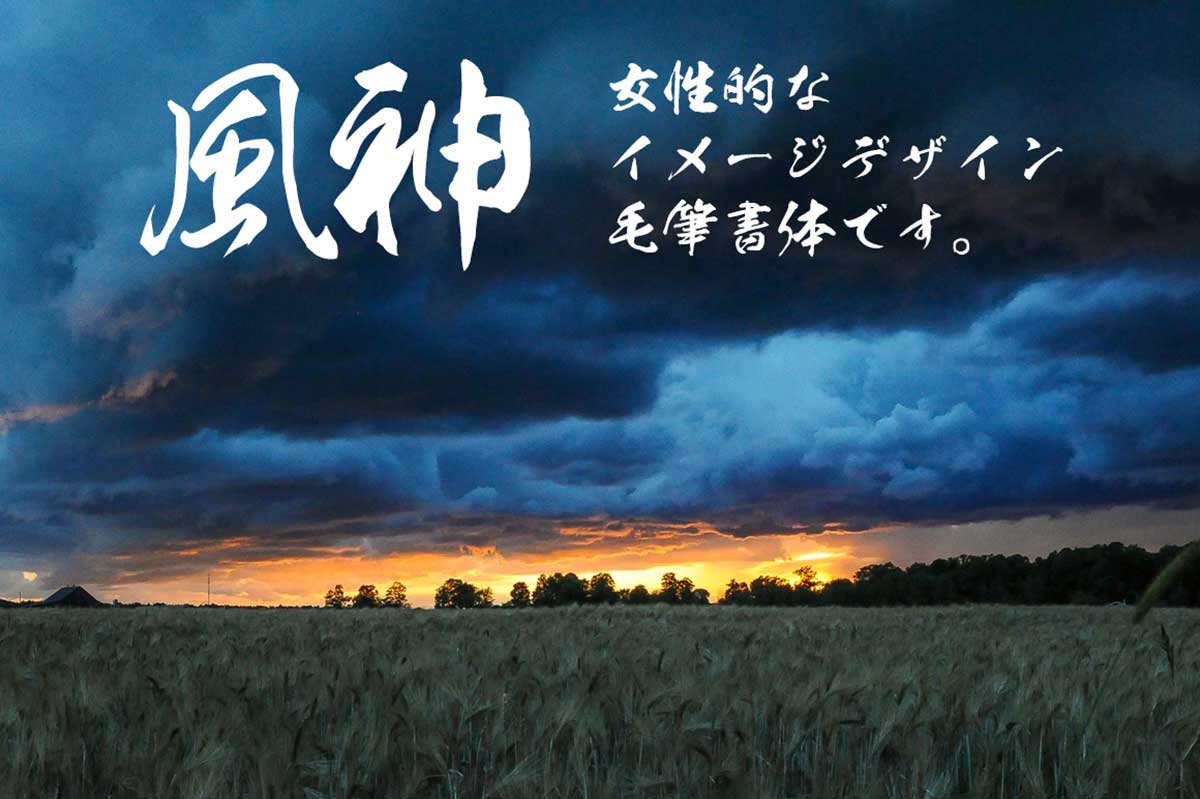
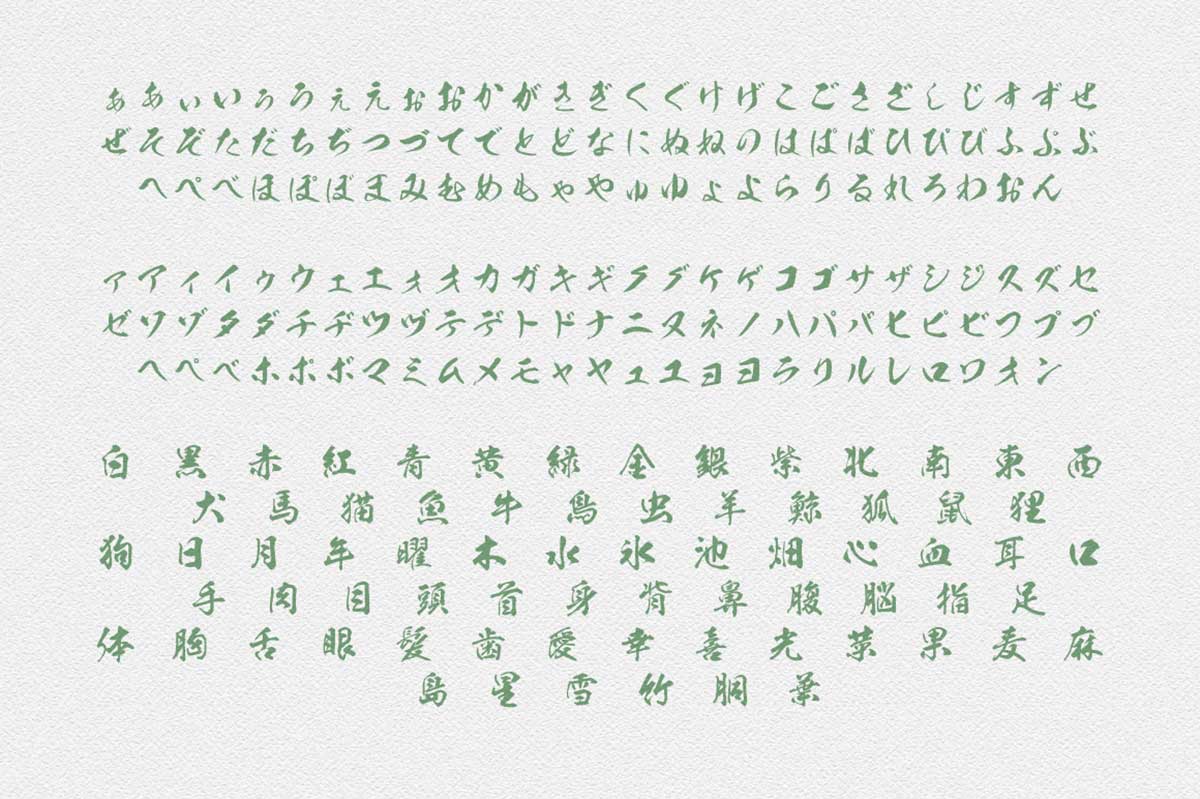
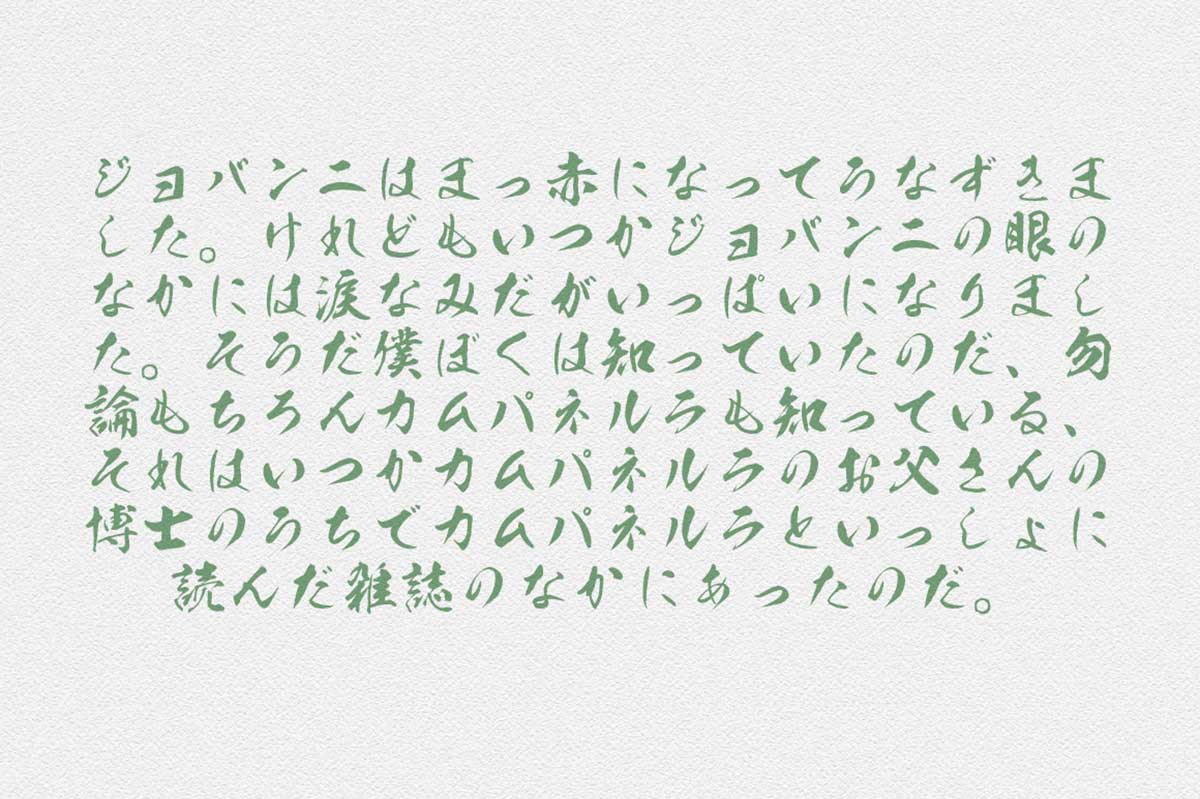
雷神書体
男性的なデザイン毛筆書体(フォント)です。
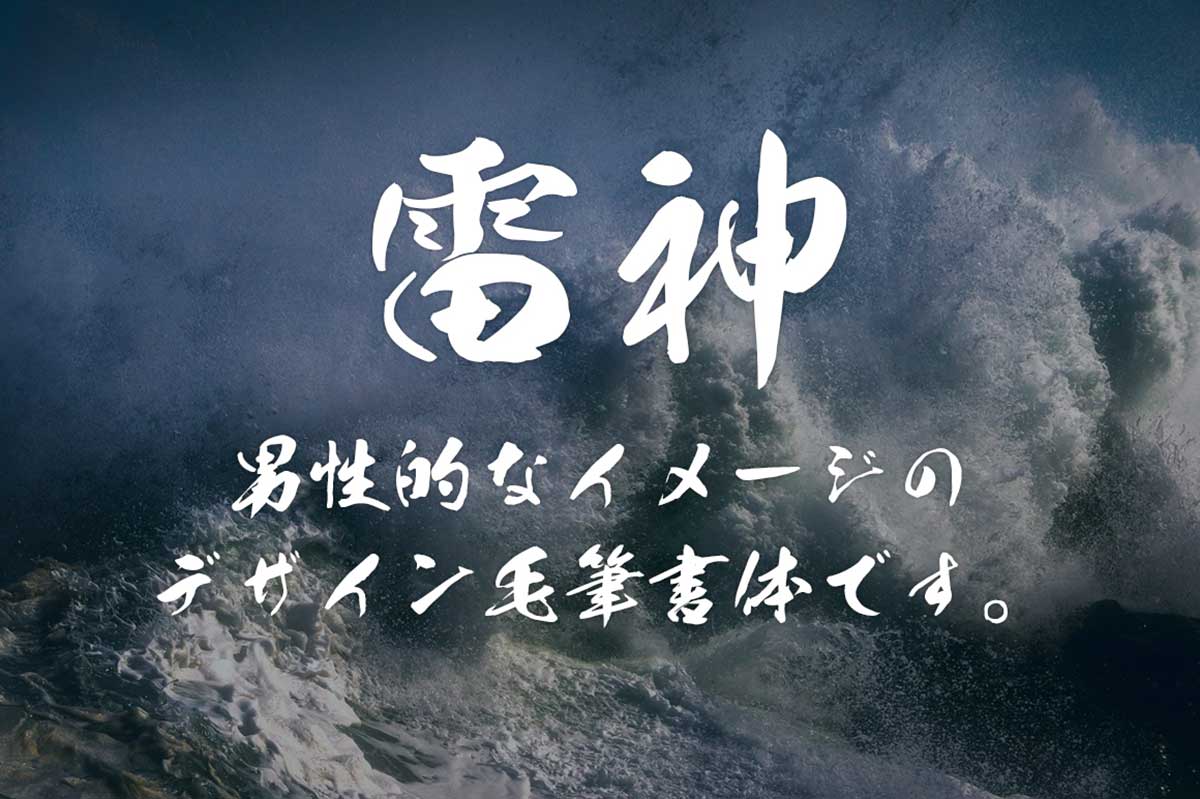
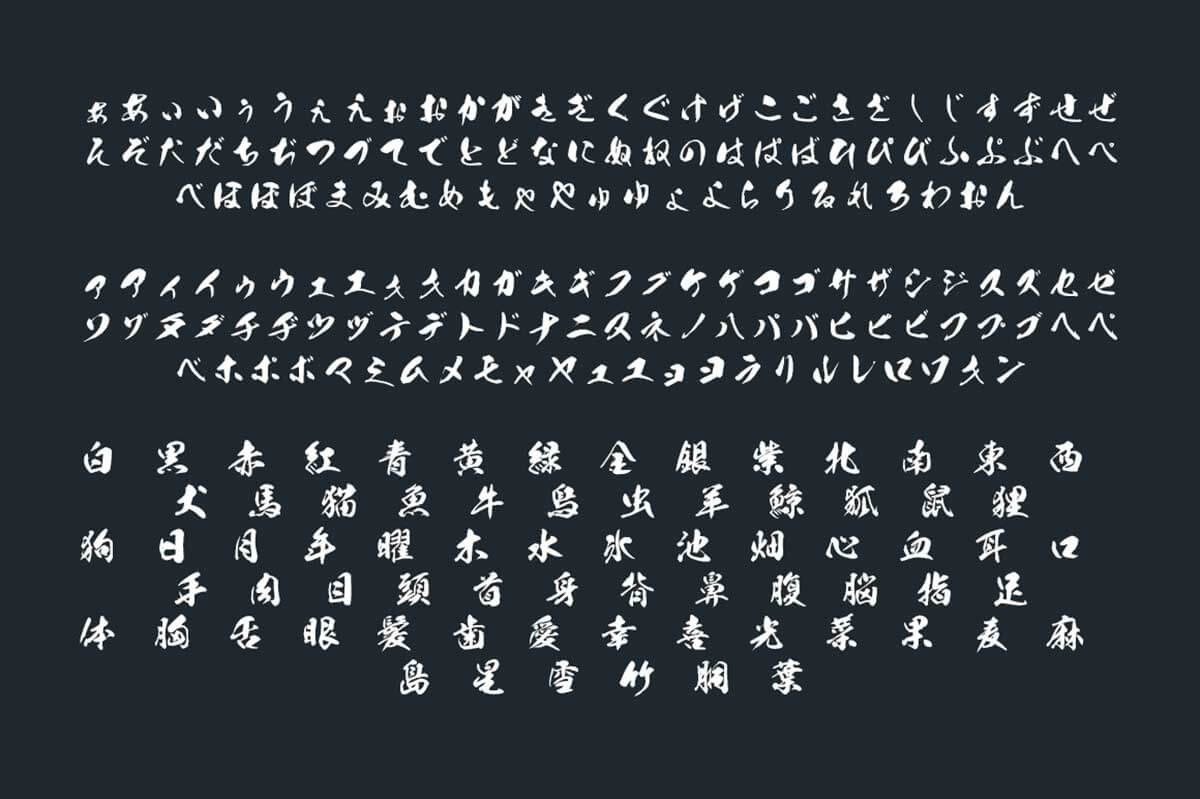
龍神書体
荒々しい龍を彷彿とさせる書体(フォント)です。
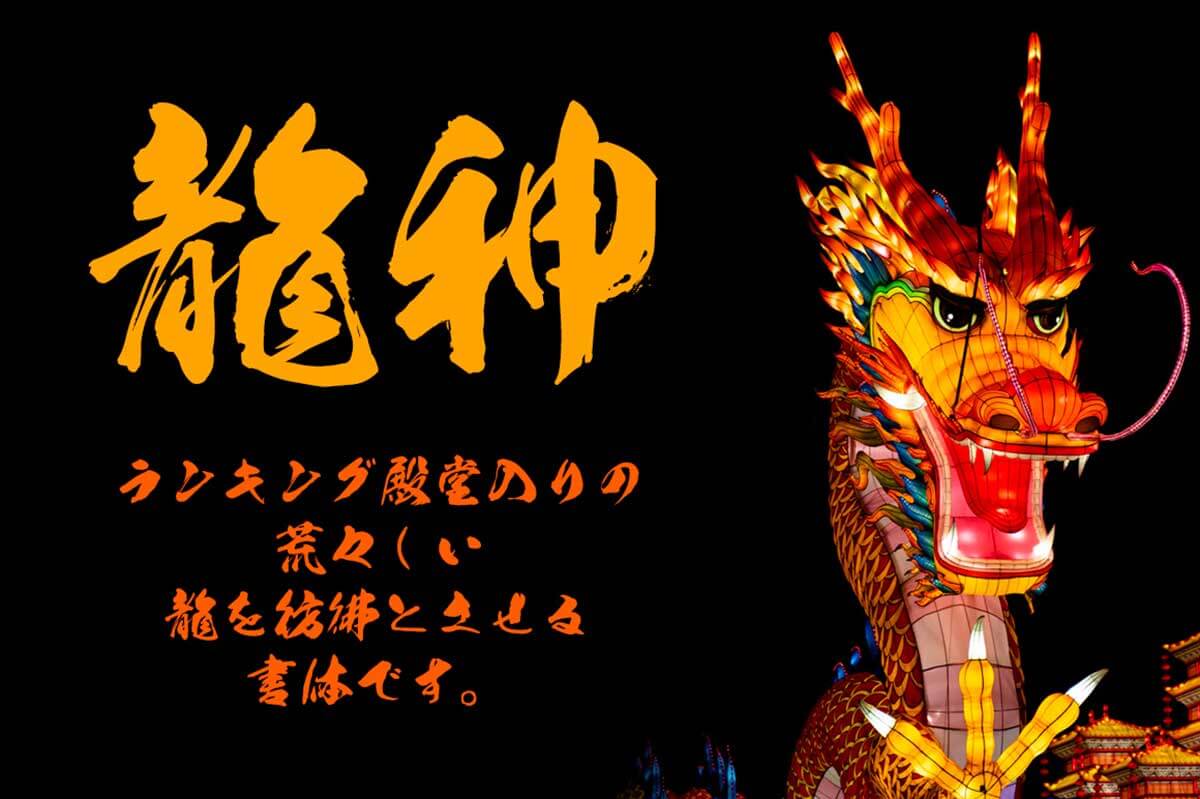
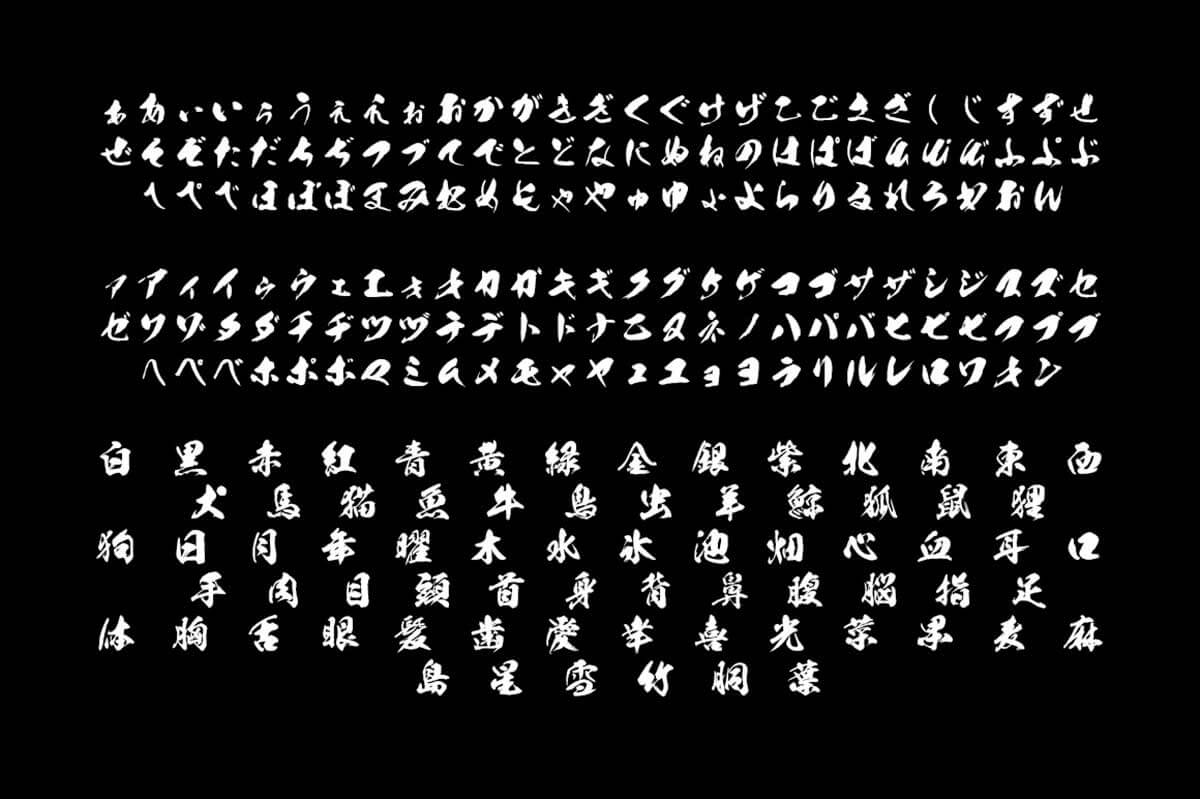
文龍書体
手紙などの小さな文字に合うように仕上げた流れるようなラインを持った基本書体です。
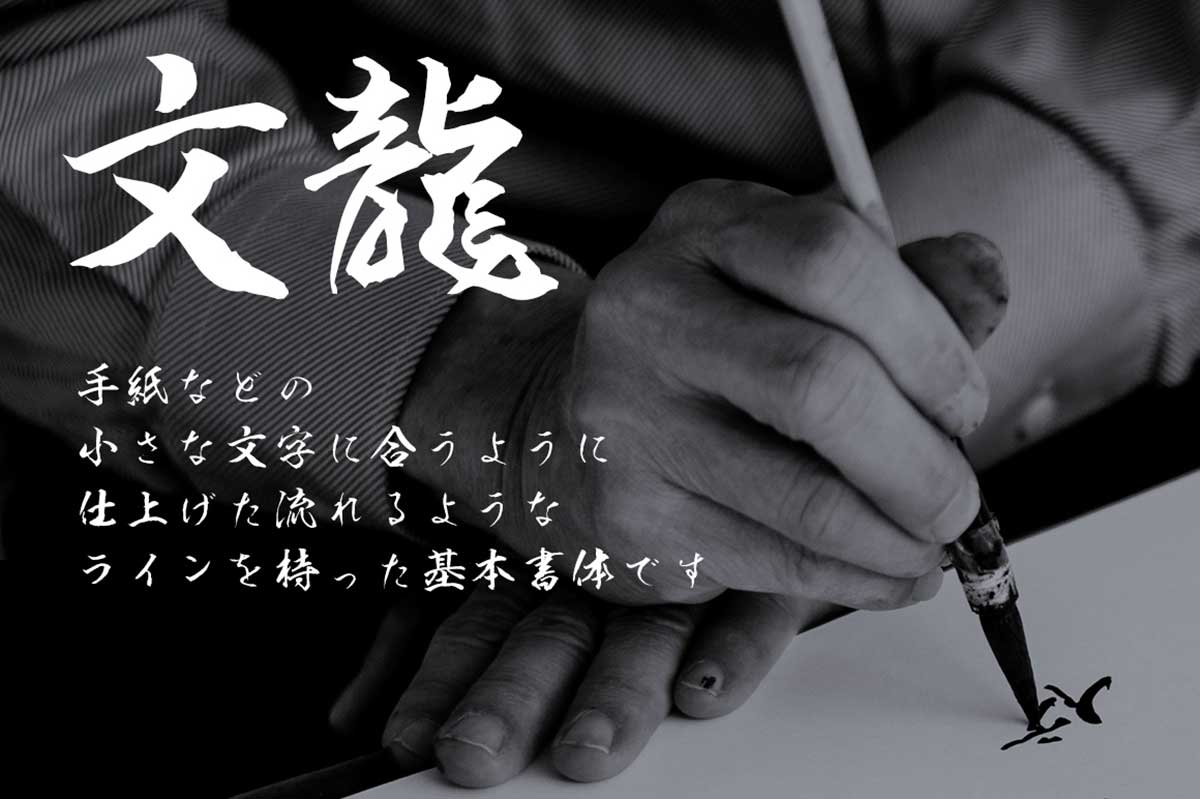
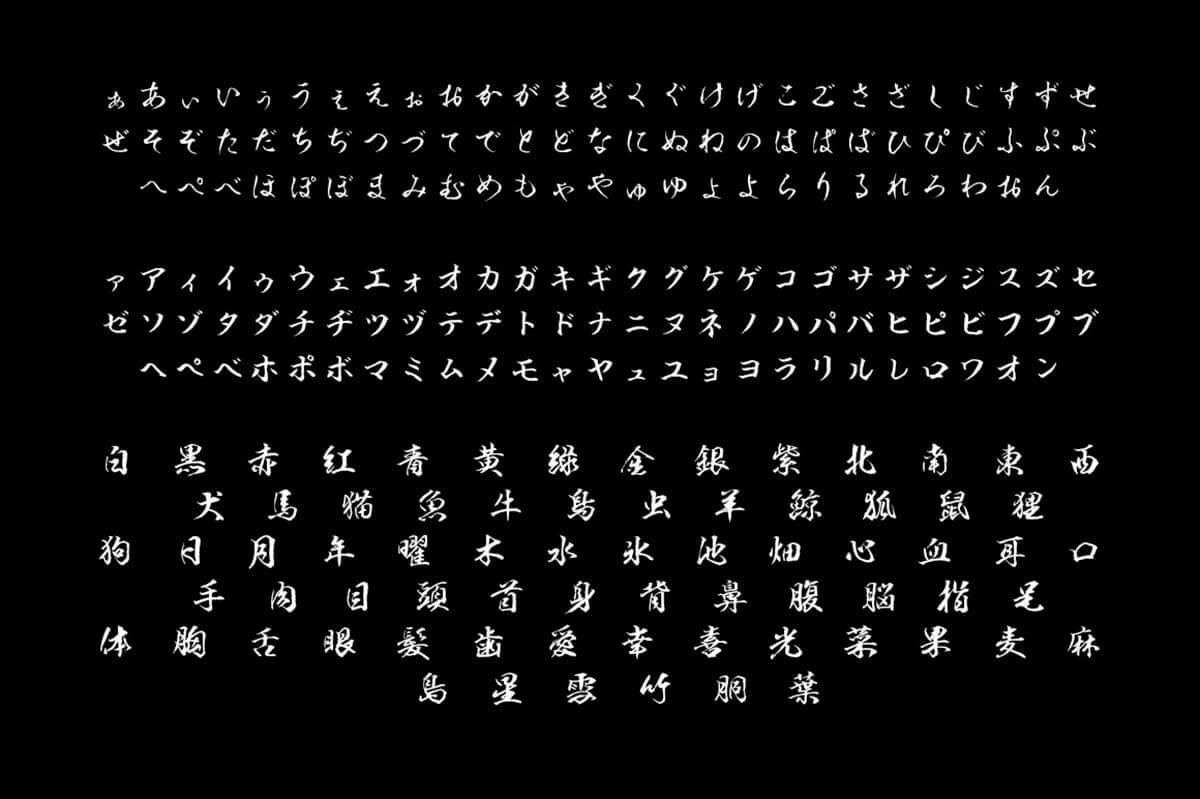
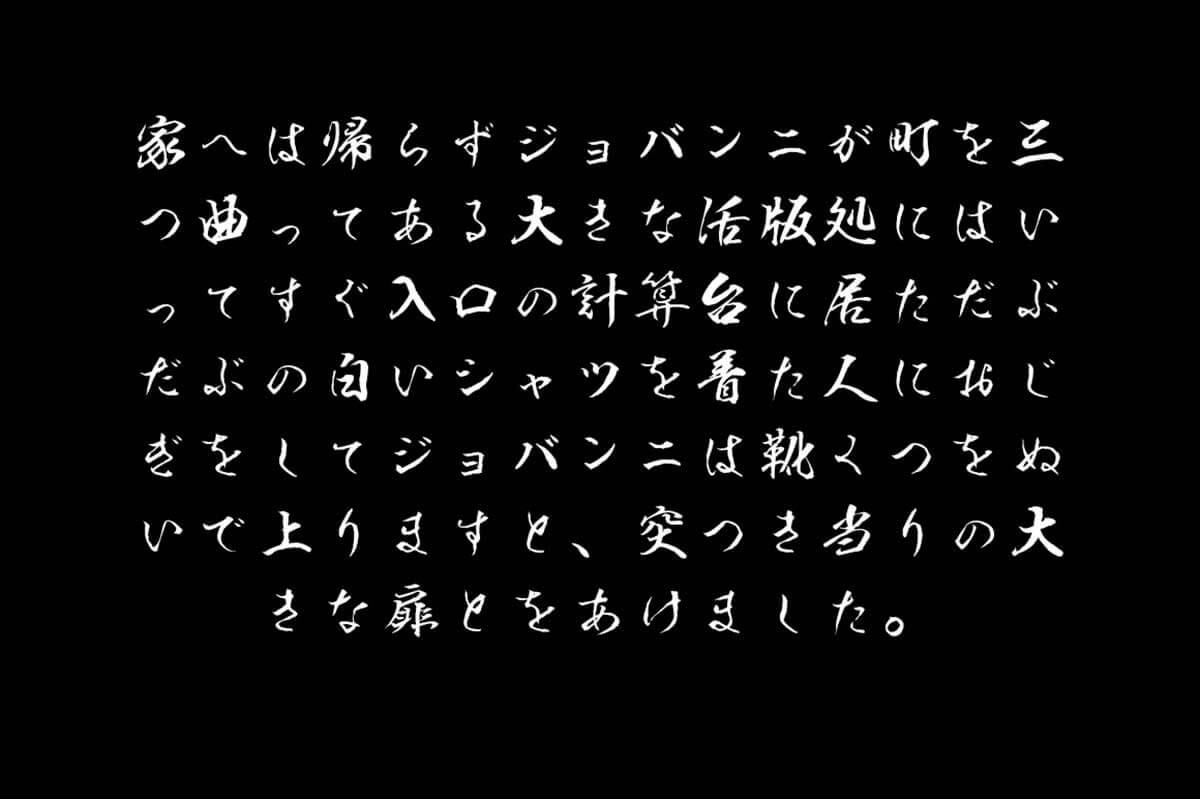
昇龍書体
正楷書に近いオリジナルの毛筆書体(フォント)です。